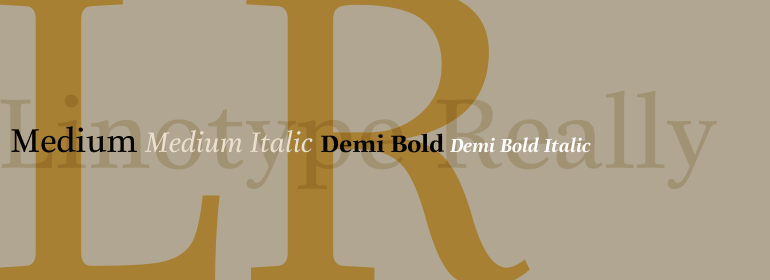
Linotype Really™
Linotype Really™,这款字体结构工整、笔画清晰,兼顾美观与易读性,适用于标题、正文、海报、包装、LOGO 等多种场景。字形优雅稳定,风格百搭耐看,适配日常排版与创意设计,让文字呈现更舒适、更具质感。Linotype Really™一笔一画,皆是细节,以均衡的比例、流畅的线条打造舒适视觉体验,字形端正大气,风格简约现代。无论是商业设计、品牌宣传还是日常排版,都能轻松驾驭,让文字更有格调与力量。Linotype Really™字体下载。
字体品牌: Linotype(Monotype) 设计师:Munch,Gary 字体分类:衬线体、正文字体 字体属性:外文 字符集:Unicode 发布时间: 2018
Linotype Really, designed by Gary Munch, is a typeface family of six weights with italics and small capitals that offers a broad palette of expressions to draw from, sensibly light to brightly stentorian. The moderate-to-strong contrast of the vertical to horizontal strokes recalls the Transitional and Modern styles of Baskerville and Bodoni, and the subtly obliqued axis of the stoke weight recalls the old-style faces of Caslon. A strong belt of sturdy serifs completes the Realist sensibility of a clear, readable, no-nonsense text face whose clean details offer the designer a high-impact display face.